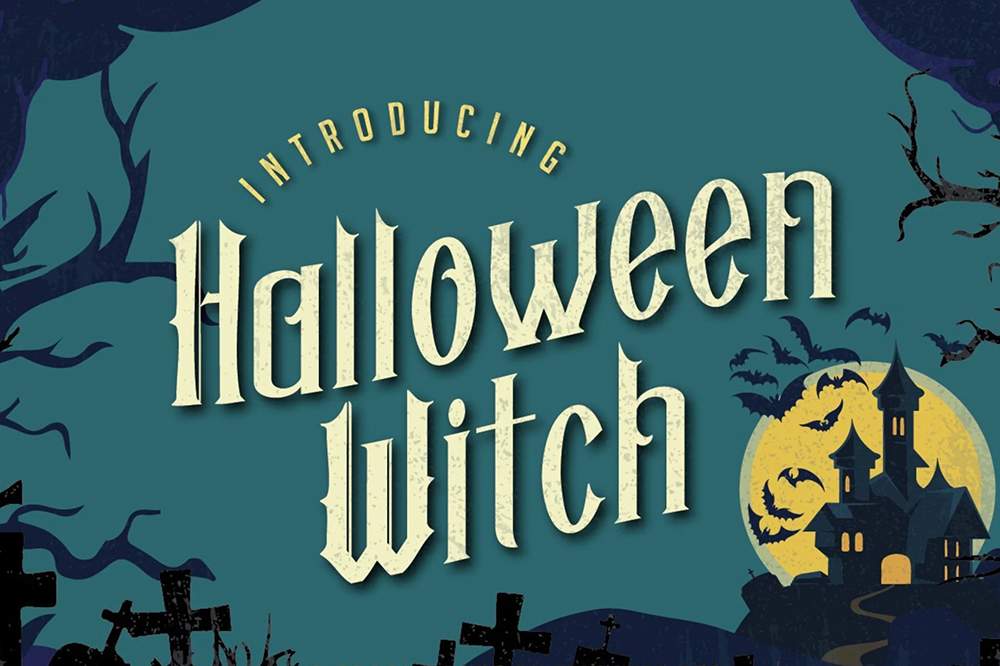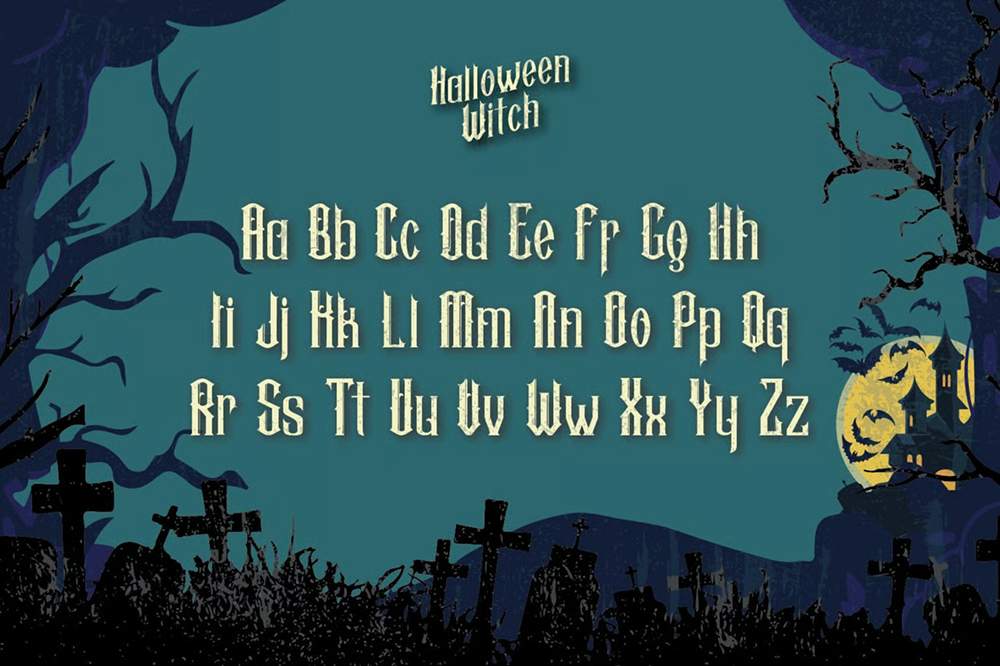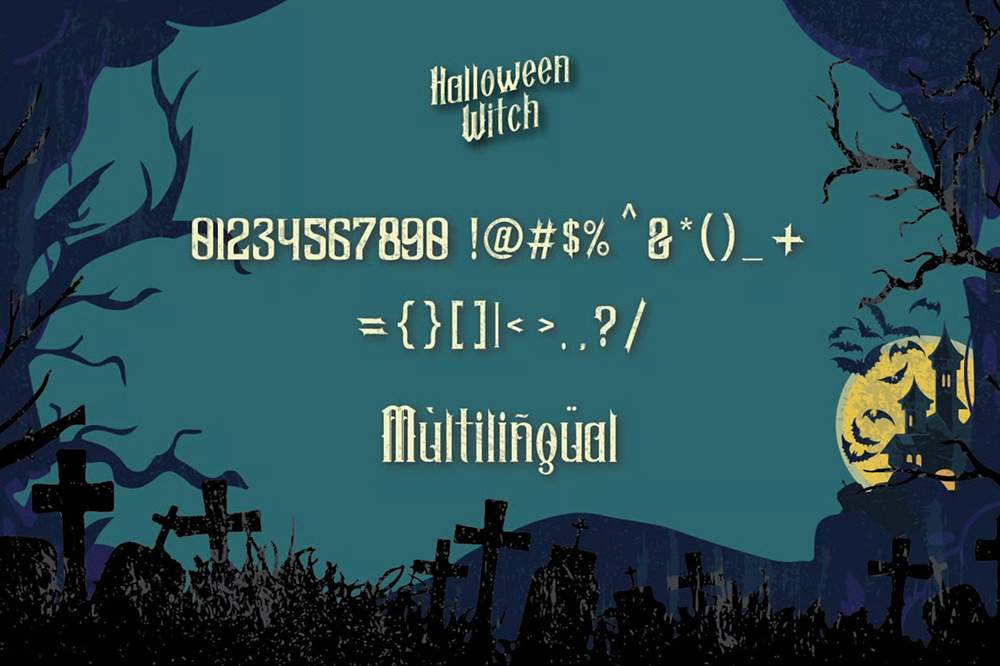
دانلود فونت انگلیسی Halloween Witch Font
فونت پرمیوم و انگلیسی Halloween Witch Font یک فونت نمایشی ترسناک و قدیمی است. این فونت دراماتیک را به طرحهای مورد علاقه خود اضافه کنید و ببینید که چگونه آنها را برجسته میکند.
مزایای استفاده از فونت لاتین Halloween Witch چیست؟